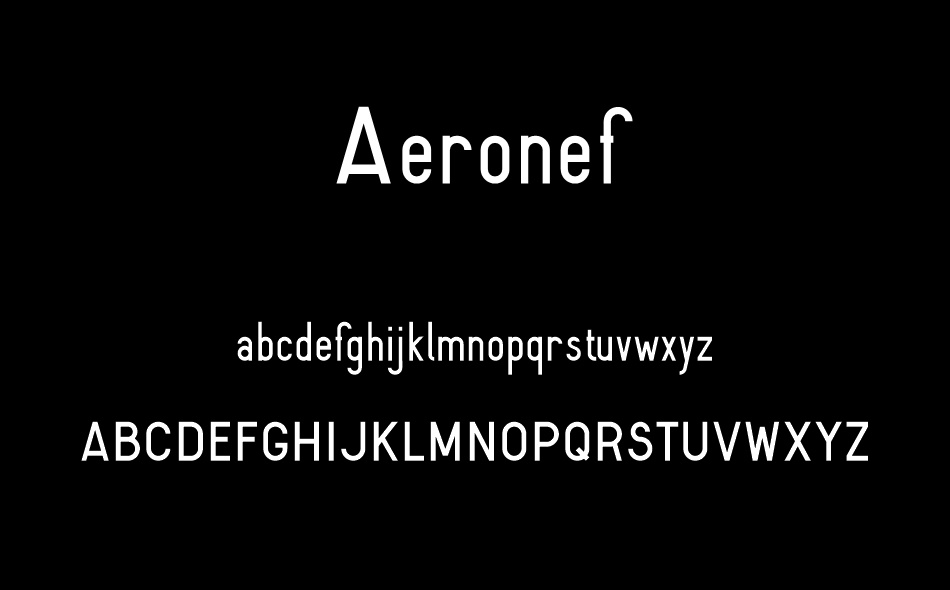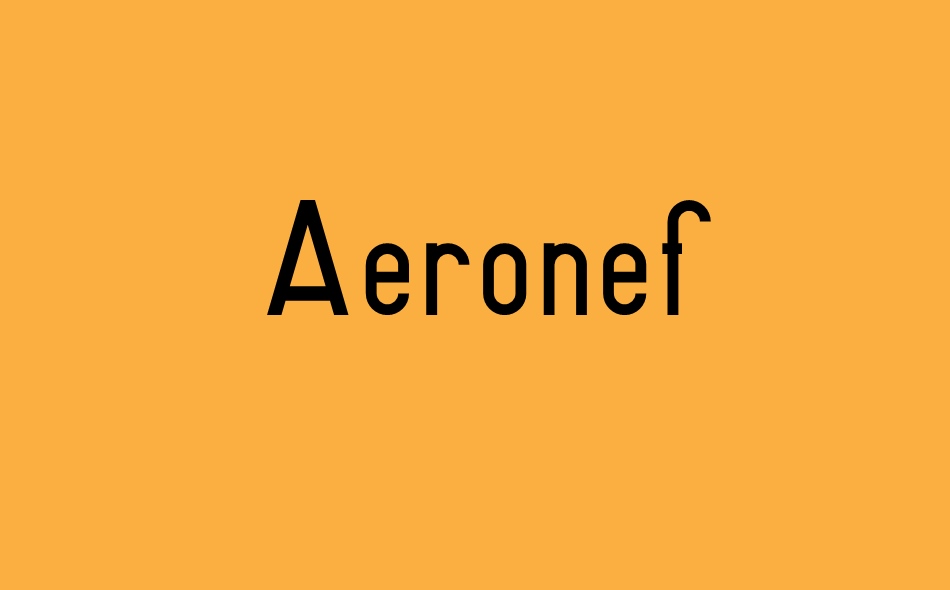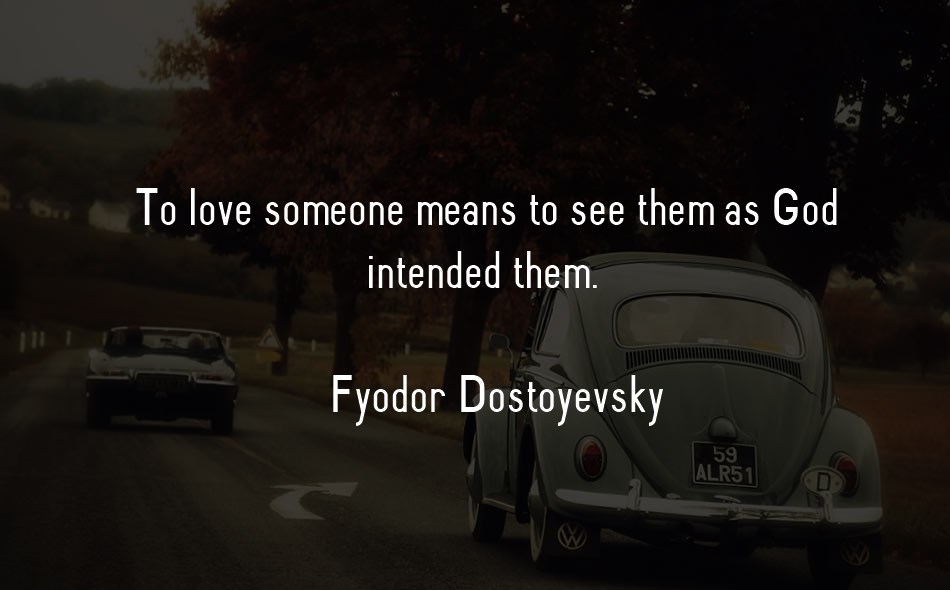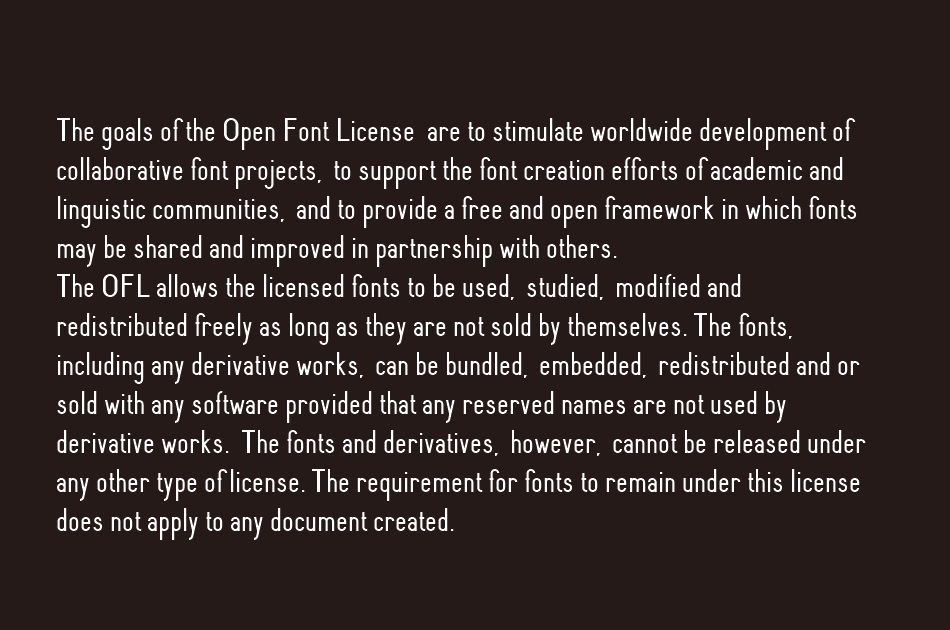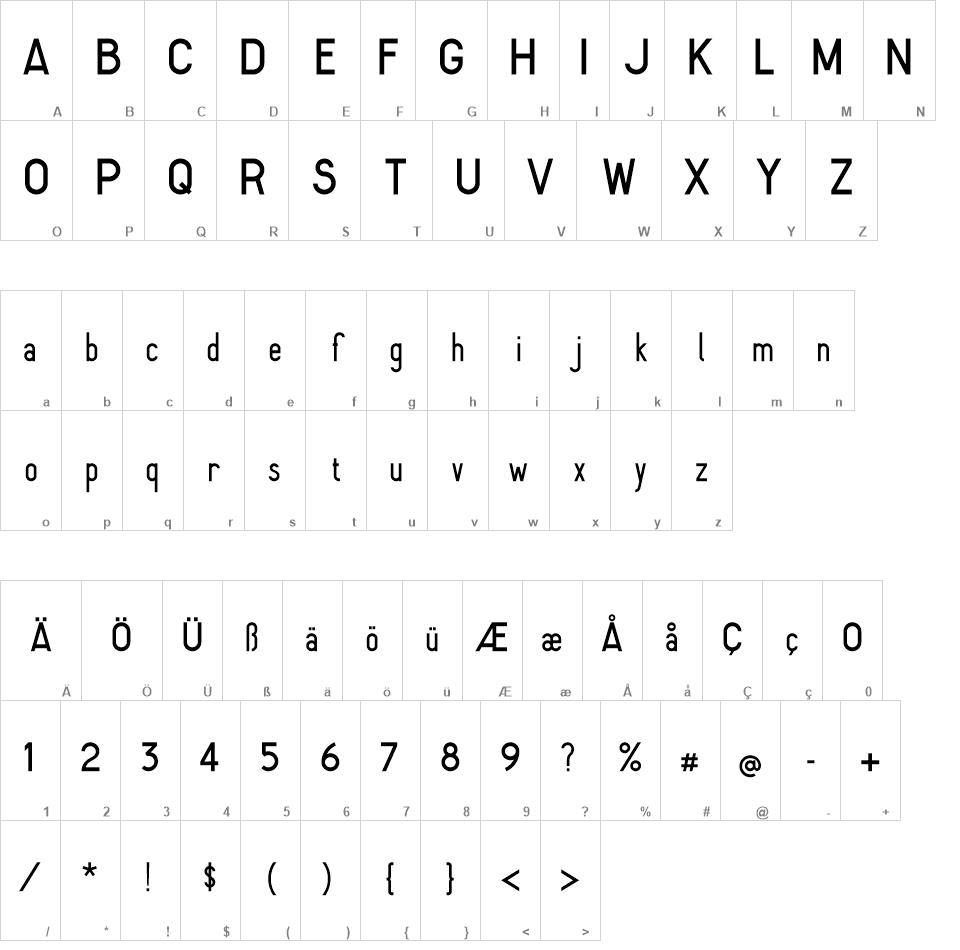
Aeronef font
Dies ist die Normschrift bei Airbus. Mit ihr werden also praktisch alle Beschriftungen iun Airbus-Flugzeugen ausgefhrt. Sie entstand nach einer original Musterzeichnung. Achtung: Diese Schrift lsst sich nur mit Software zu 100% nutzen, welche OpenType-Funktionen untersttzt.
Aéronef (Flugzeug)
Das ist die Normschrift der europäischen Luftfahrtindustrie.
Es war eine Anfrage eines Schildermachers, der nur eine
Musterzeichnung bekommen hatte, aber niemand konnte einen
Font zur Verfügung stellen.Musterzeichnungen sind ja genau
mein Ding.
Und dann hat diese Schrift auch noch
lustige Regeln: l hat nur alleinstehend ein Häkchen für das Literzeichen, , (z.B. 5l
lauwarme Milch)
f  hat vor hohen Schriftzeichen einen kürzeren Haken, (siehe fe fh)
und irgendwie sollen Brüche möglich sein. Das schreit
nach OpenType-Funktionen…
Die Brüche mit  Zähler 2, 4, 8, 16,   32 , und
Nenner 1,3,5,7,9,11,15, 17, 19, 21, 23, 25, 27,  29, 31  .
zwischen Ganzzahl und Bruch ein Leerzeichen ergibt z.B. 5 ¾“
Beliebige Brüche:Doppelt Akut tippen,dann den Bruch
schreiben: ´ ´  3  4  5   /  7  7  =    345/77
Und d ANN ist d A no CH die Spezial K APITÄLCHEN  Funktion:
Die ist zwar nicht Nor M, aber irgendwie Cool
Einfach doppelt Akut vor den jeweils 1. GROBßUCHSTABEN.
Und  nach oder zwischen 2  Großbuchstaben ergibt groes ß!